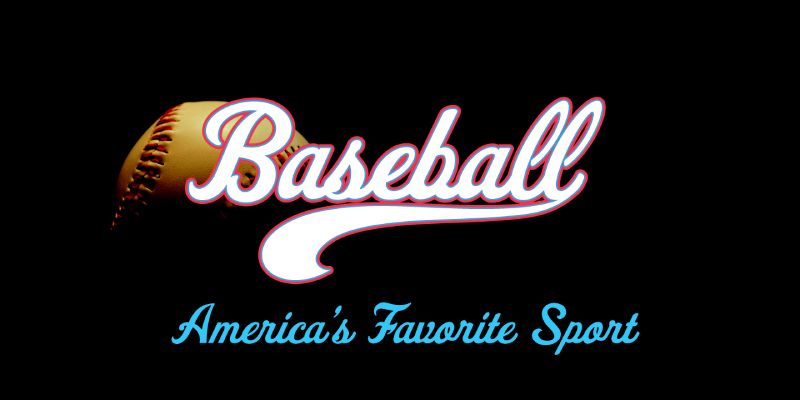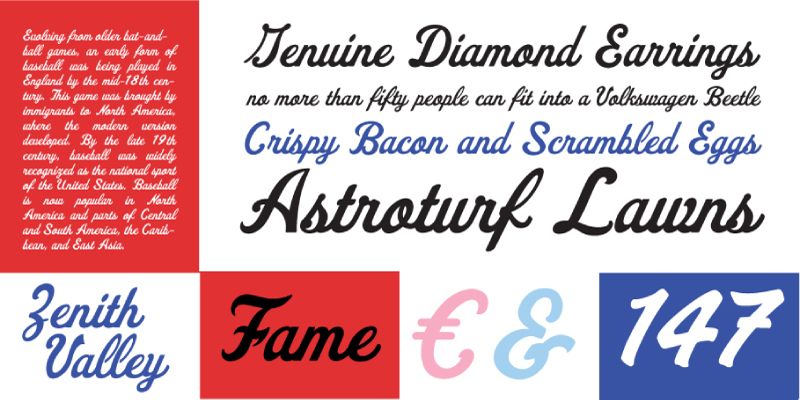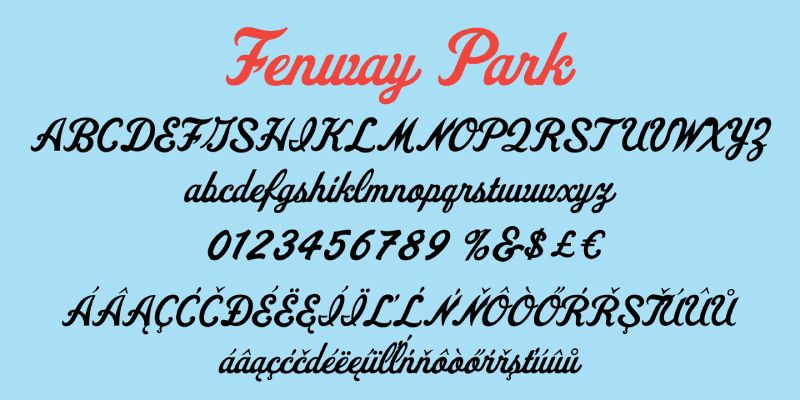
Basierend auf den Schriftzügen der Logos von Leichtathletik- und Sportmannschaften (insbesondere Baseball) fängt Fenway Park die ganze Nostalgie und den altmodischen amerikanischen Charme seines Namens ein.